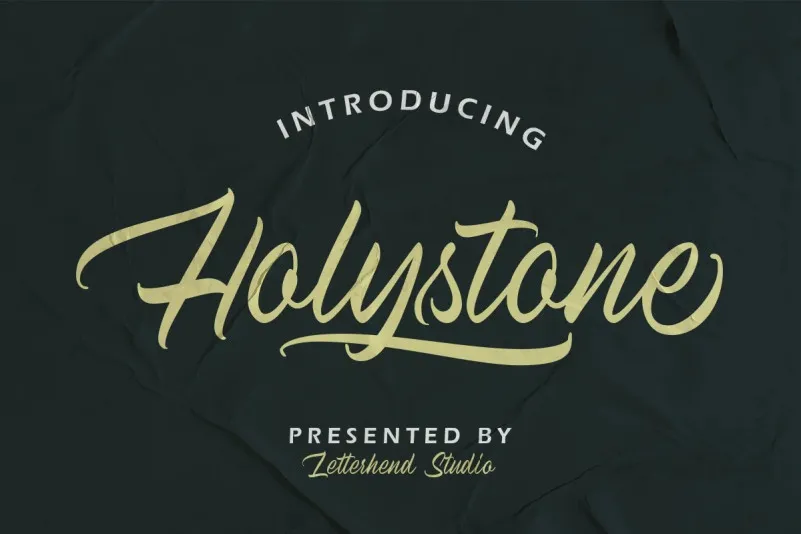
A Holystone é uma fonte de estilo script moderno com um toque refinado que transmite elegância clássica e luxo. Perfeita para criar headlines chamativas, postagens e stories no Instagram, logomarcas, capas de livros, cartões de convidados, embalagens, moda, maquiagem, materiais de escrita, etiquetas ou qualquer tipo de propósito publicitário. Suave e sofisticada, a Holystone se destaca em design gráfico. Suas linhas suaves e detalhes finos criam um ar delicado que é ideal para uma variedade de aplicações. Além disso, sua versatilidade torna-a uma escolha inteligente para qualquer projeto em que você deseje agregar elegância ou estilo minimalista ao seu design. Seja para um projeto editorial de revistas e livros, cartões de decoração de casamento, embalagens de produtos cosméticos, materiais de escrita, etiquetas de embalagem ou até mesmo campanhas publicitárias, a Holystone é uma opção sólida que criará um impacto visual imediato. Sua sofisticação e modernidade combinam para tornar a fonte uma ferramenta indispensável no seu armário de recursos gráficos.